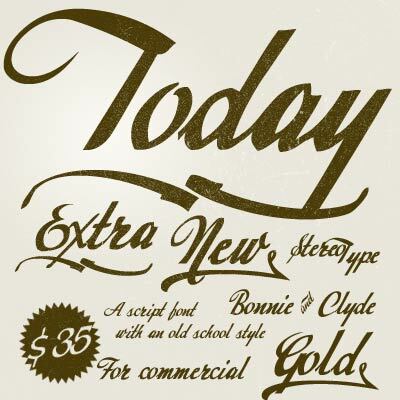
Today od StereoType to darmowy krój pisma typu brush script, przywodzący na myśl szybki szkic modowy. Litery pochylają się do przodu w jednym, płynnym ruchu, łącząc szerokie, malarskie krzywizny z ostrymi, zwężającymi się końcówkami. Długi ogonek przy literze „y” nadaje całemu krojowi luźny, dynamiczny charakter, zamiast sztywnego, formalnego wykończenia.
Naturalnie pasuje do identyfikacji wizualnych butików, nagłówków w magazynach, opakowań produktów kawiarnianych, zaproszeń na wydarzenia czy grafik do social mediów, wszędzie tam, gdzie krótkie hasło potrzebuje ruchu i odręcznego akcentu. Jako darmowy font, świetnie sprawdzi się też przy szkicach logotypów, szybkich nagłówkach czy inicjałach, ponieważ jego pociągnięcia pędzla sprawiają wrażenie spontaniczności, nie tracąc przy tym na czytelności.